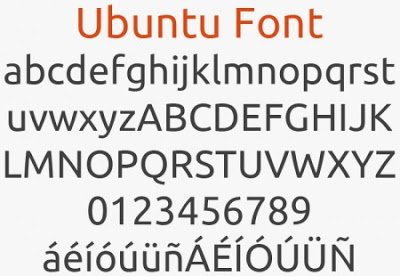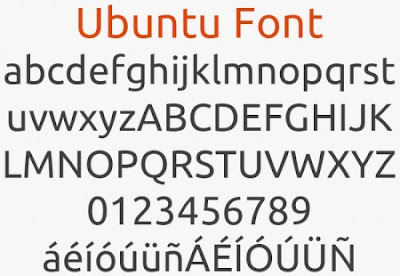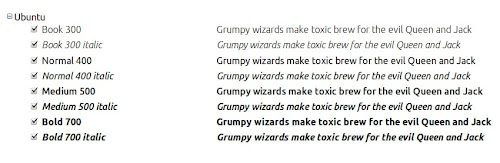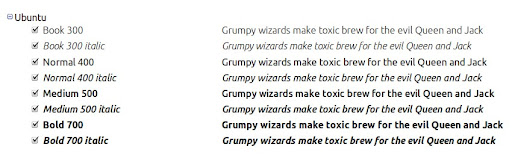
Canonical negli scorsi mesi ha rilasciato i font Ubuntu i quali sono presenti di default da Ubuntu 10.10 Maverick e sulle release successive.
I nuovi font Ubuntu oltre ad essere veramente molto belli sono anche utilizzati da molti siti (tra questi anche lffl) essendo anche presenti in Google Font Directory. Chiunque può quindi utilizzare i Font Ubuntu essendo rilasciati sotto licenza GPL quindi oltre ad utilizzarli liberamente possaimo anche modificarlo e ridistribuirlo senza problemi.